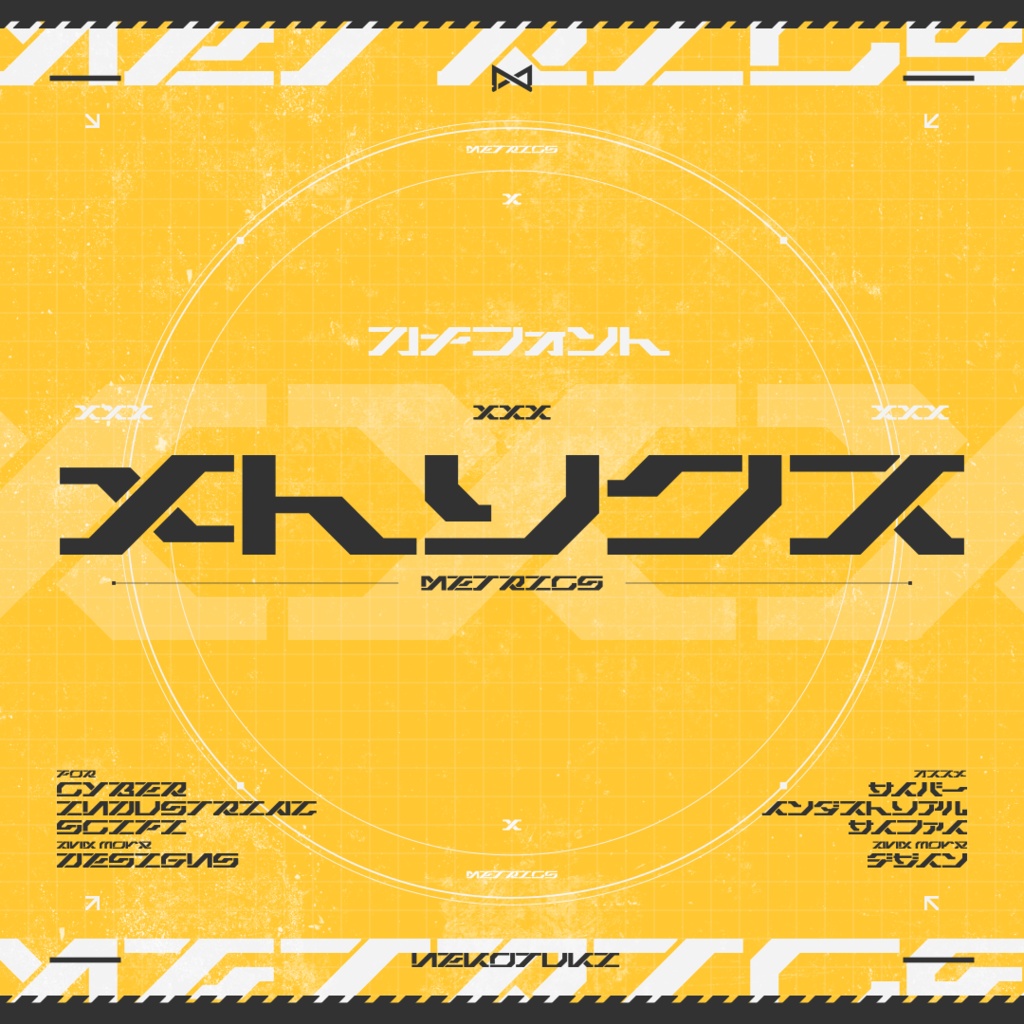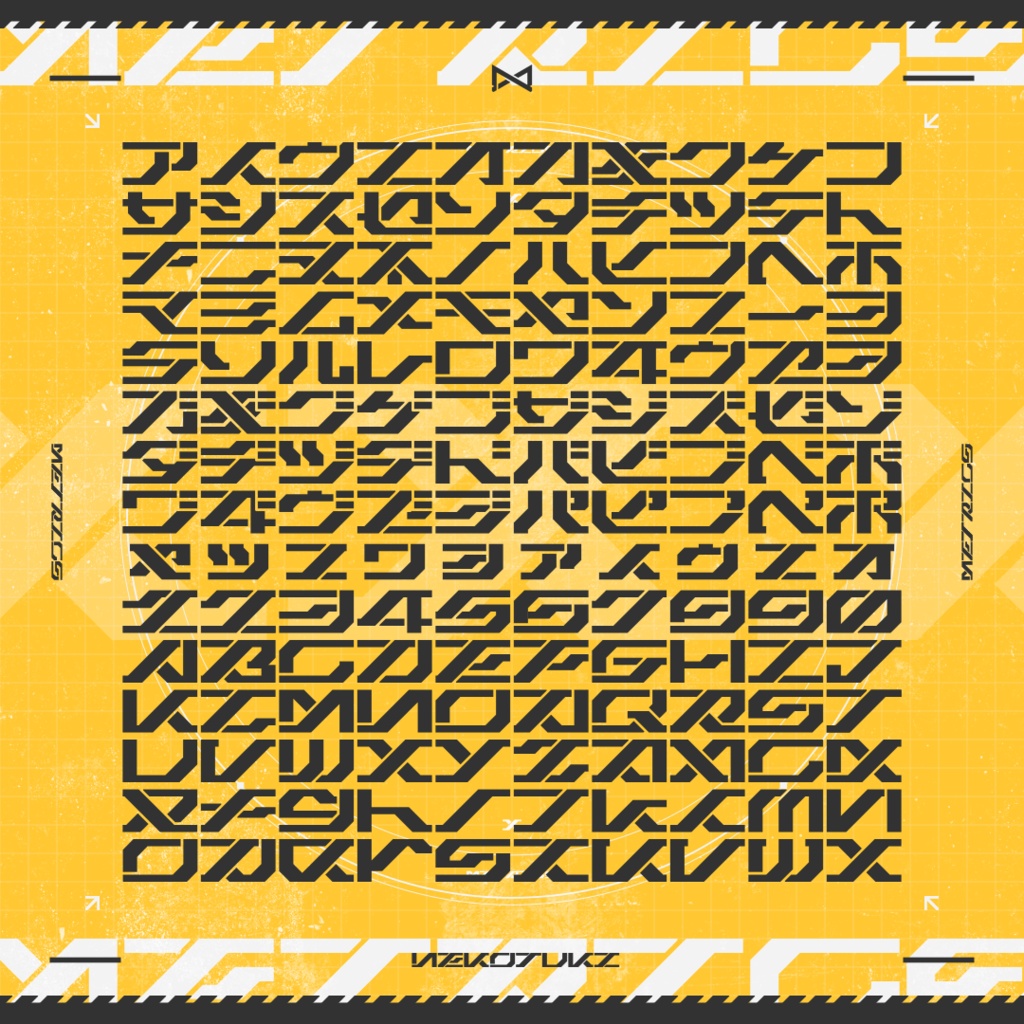
カナフォント『メトリクス』 - Japanese Katakana Font "METRICS"
日本語カナフォント『メトリクス』 全て同じ規格に沿って設計された、横長でメカニカルな造形が特徴のフォントです。 サイバー・インダストリアル・SFといったデザインへの使用を推奨しております。 ロゴとして使用するのはもちろん、デザインのディティールとしての使用にも適しております。